黑體
思源黑體 Noto Sans
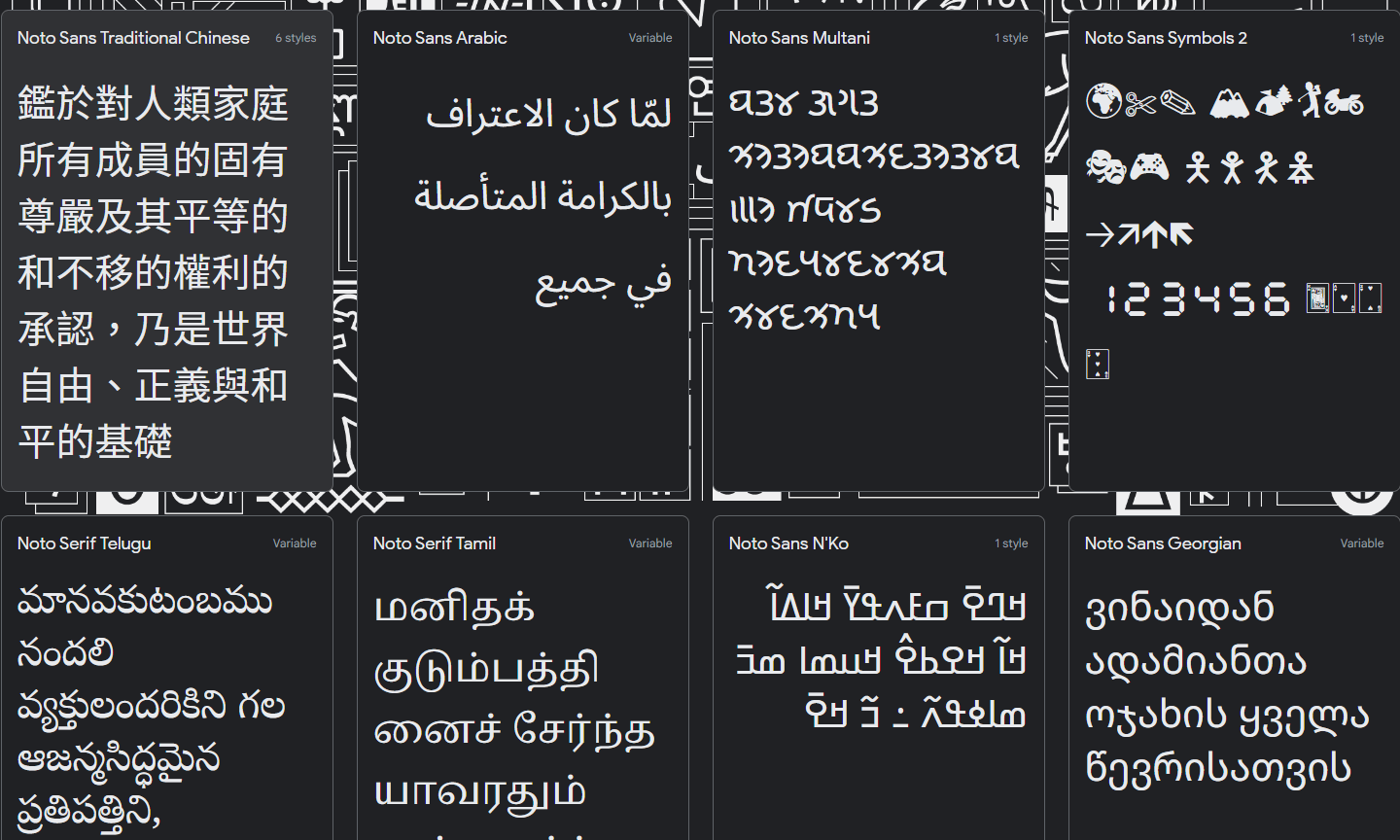
源石黑體 Genseki
「源石黑體」是基於思源黑體的開放原始碼中文字型。
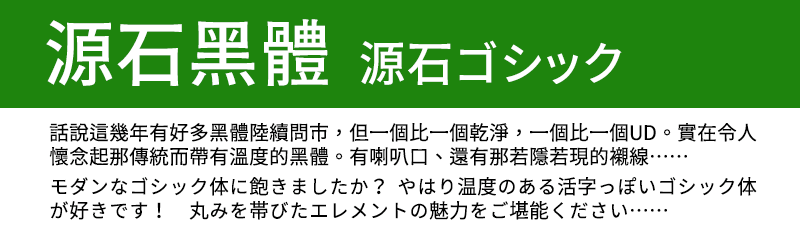
台北黑體 TaipeiSans
台北黑體基於 Adobe 所開發、發布的思源黑體改作而成。改作則基於思源黑體的 SIL Open Font License 1.1 授權。
源樣黑體 Genyog
「源樣黑體」是基於思源黑體的開放原始碼中文字型。 採用思源黑體韓文(KR)版本為主的字符,配合繁體中文慣用的置中標點,可排版傳統印刷體風格的文件。
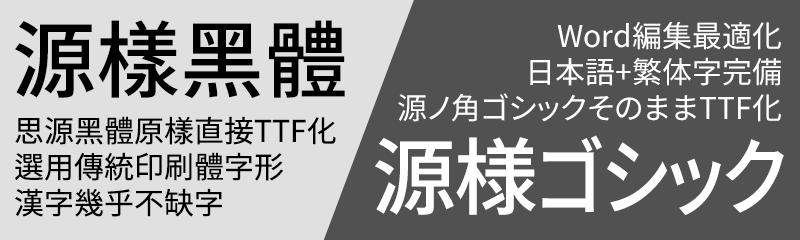
資源圓體 Resource Han Rounded
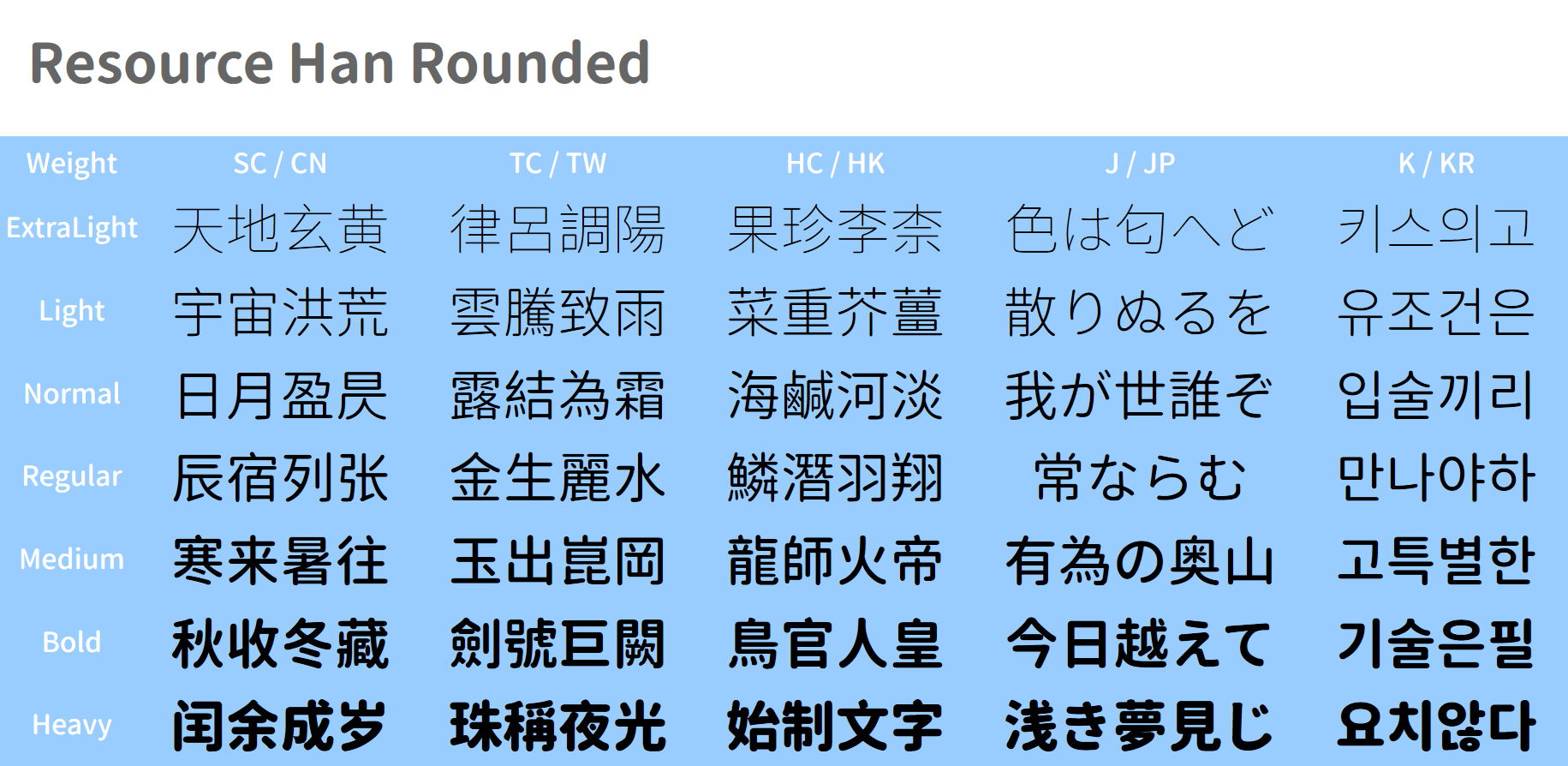
未來熒黑 Glow Sans
未來熒黑是一個基於思源黑體、Fira Sans 和 Raleway 的開源字型專案,支援簡體中文、繁體中文與日文;思源黑體的 7 字重被擴展為 9 字重,並提供了寬度系列,全家族共 44 款字型。未來熒黑繁體中文版的漢字部分係改造自思源黑體韓文版,以更接近傳統印刷習慣。
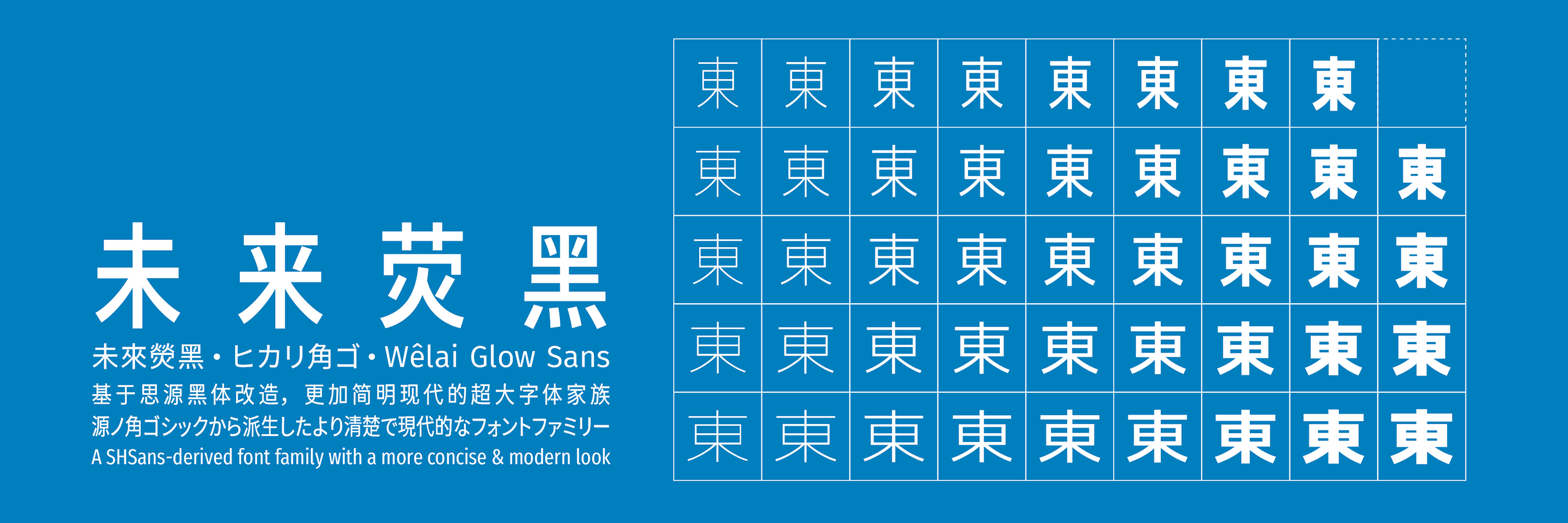
阿里巴巴惠普體 Alibaba PuHuiTi
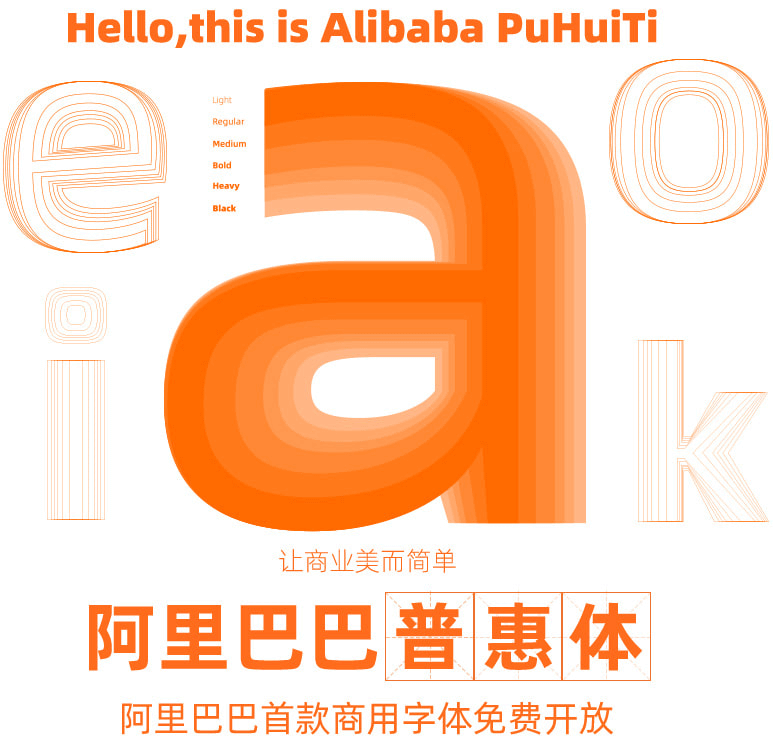
思源柔黑體 Genjyuu
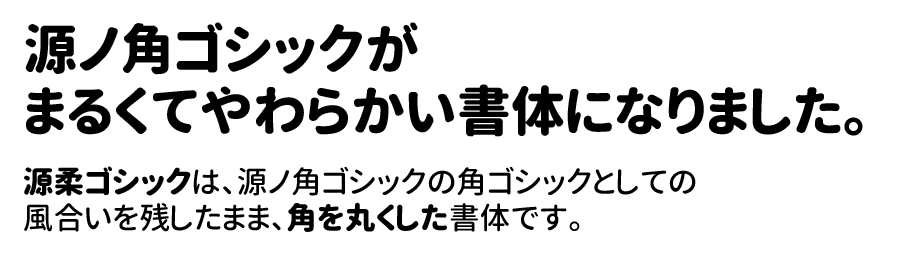
思源真黑體 Genshin
圓體
源泉圓體 Gensen
「源泉圓體」是基於思源黑體的開放原始碼中文字型。
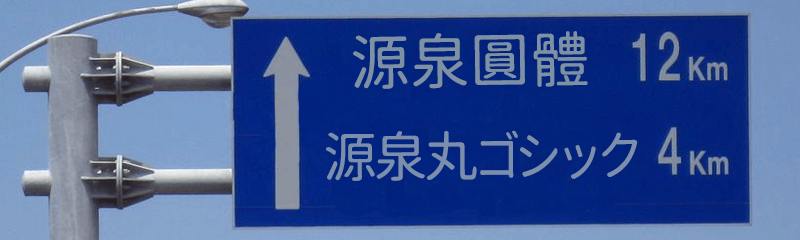
粉圓體 Huninn
「jf open 粉圓字型」是基於 Kosugi Maru 改作,由 justfont 設計師針對台灣日常應用加以優化的開源字型。歡迎大家自由應用、自由優化、自由改作!
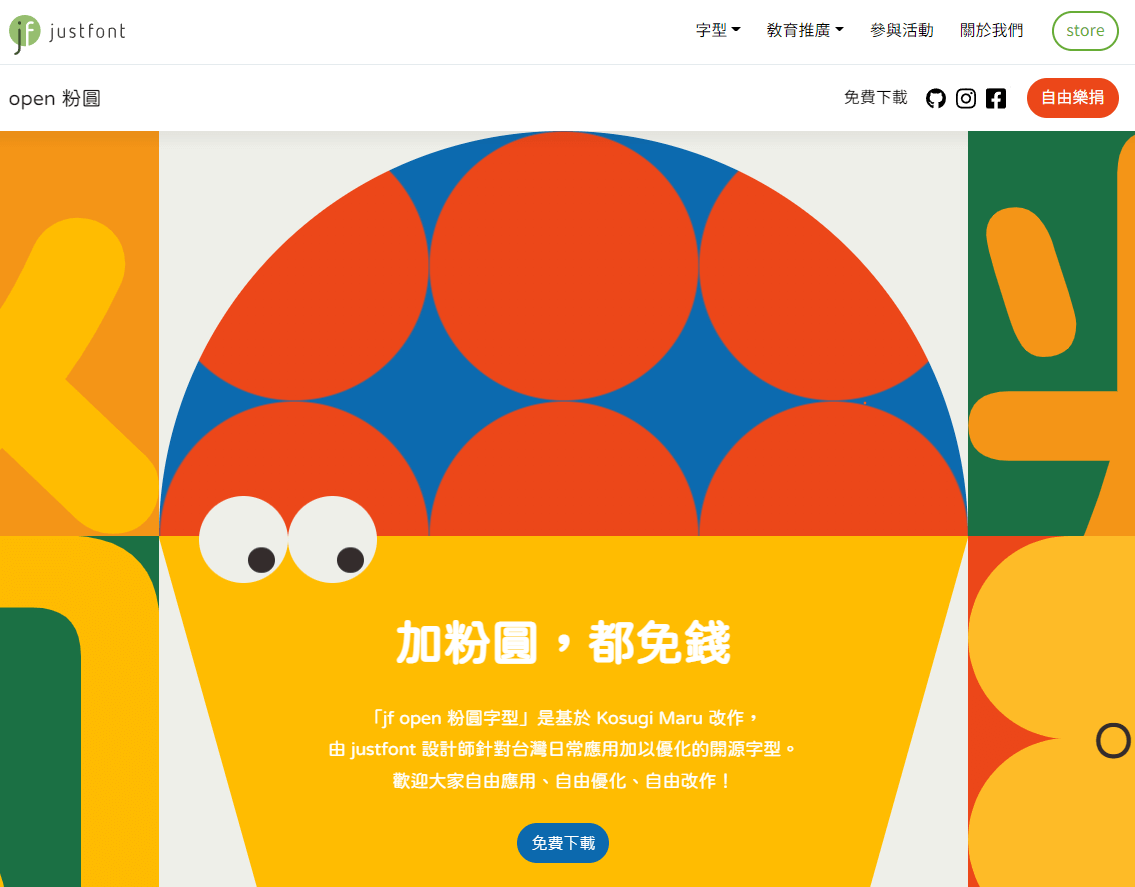
貓啃網糖圓體 Mao Ken Tang Yuan
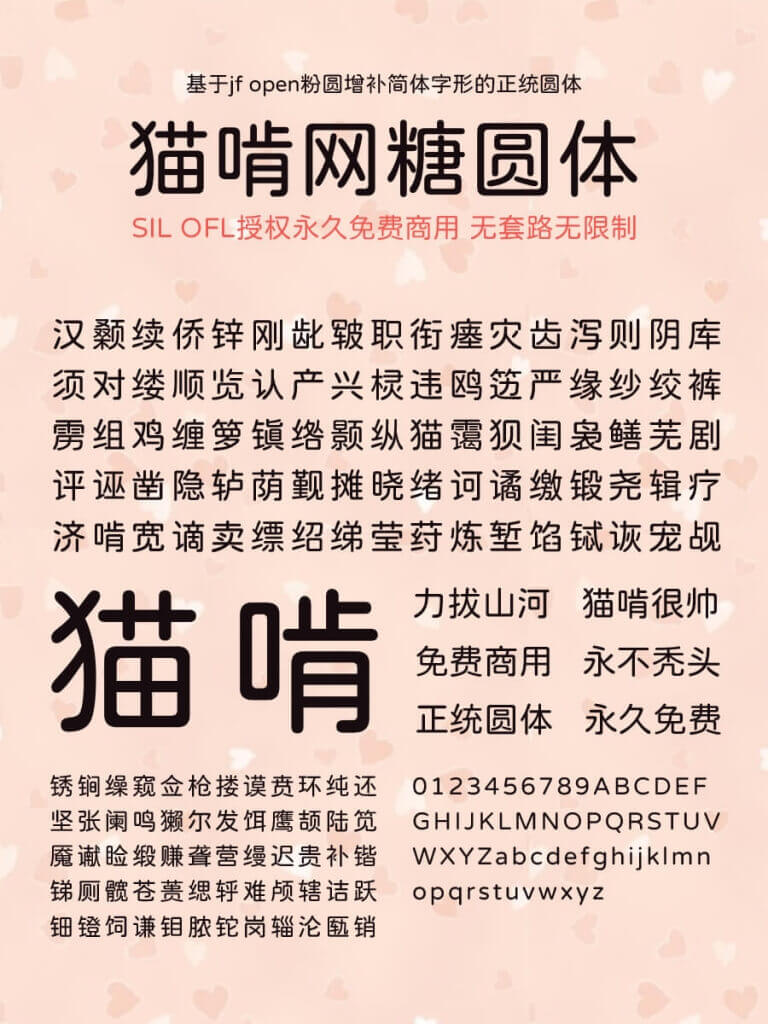
宋體
思源宋體 serif
全字庫正宋體
楷體
全字庫正楷體
明體
源樣明體 Genyo
「源樣明體」是基於思源宋體的開放原始碼中文字型。 採用思源宋體韓文(KR)版本的字符,配合繁體中文慣用的置中標點,可排版傳統印刷體風格的文件。
源流明體 Genryu
「源流明體」是基於思源宋體的而改造的開放原始碼中文字型。
源雲明體 Genwan
「源雲明體」是基於思源宋體的而改造的開放原始碼中文字型。
明朝體
源界明朝 Genkai Mincho
裝甲明朝 Soukou Mincho
手寫字形
宅在家自動筆
851手書き雑フォント 851tegaki_zatsu
kawaii手書き文字
其它字型
小赖字体 Xiaolai
濑户字体 是由日本的业余字体设计师 瀬戸のぞみ 制作,支持 JIS 第一至第四级,支持繁体和简体中文(部分)。目前最新的版本是 2014 年 9 月 24 日的 6.20 版本,原作者已经很久不更新了。
瀨戶字體 Seto
WD-XL 滑油字
字體圈欣意冠黑體